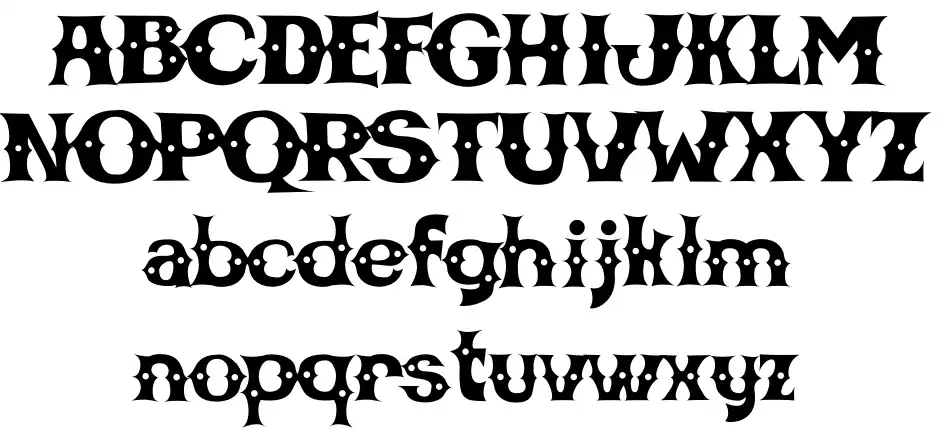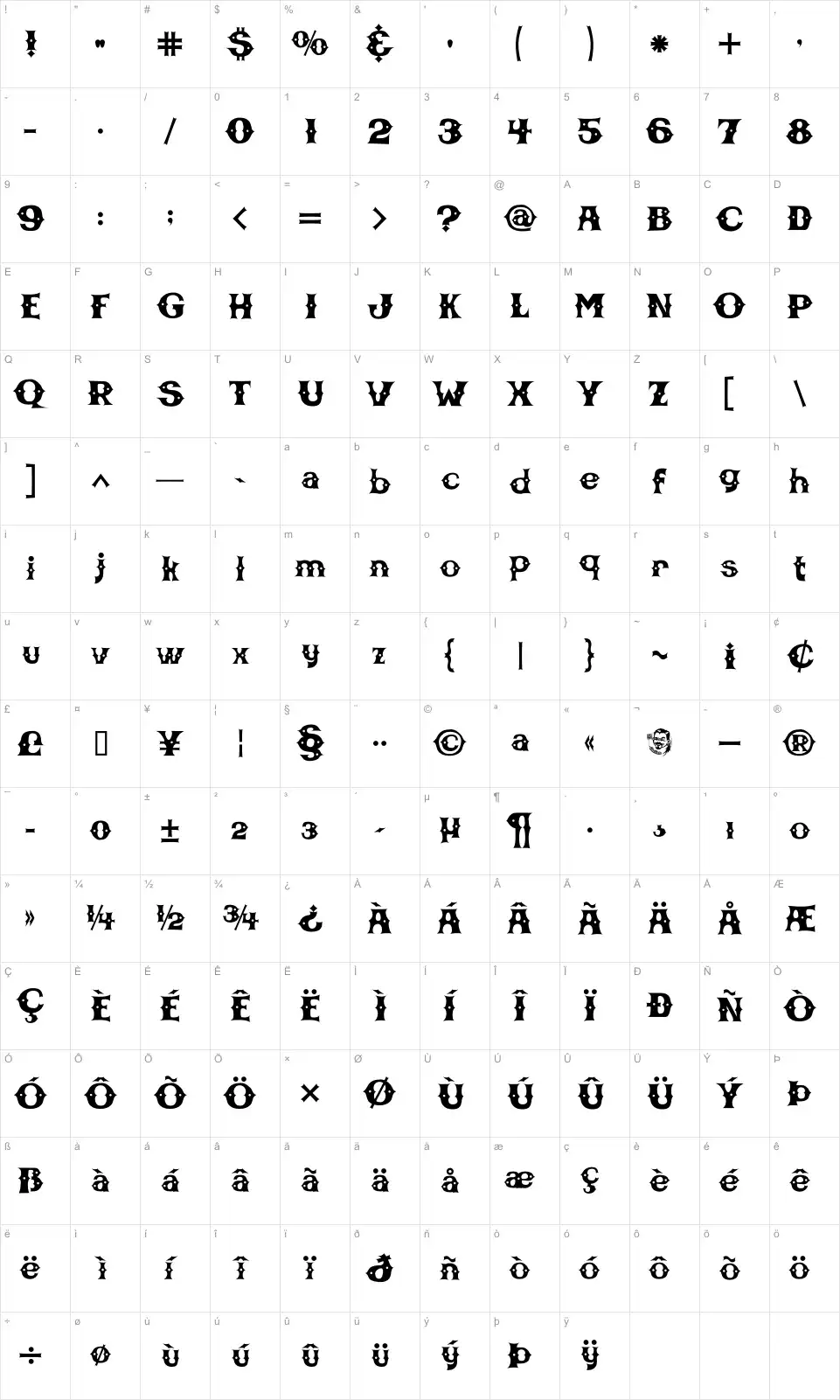
CBGB Font – Download Grátis
A CBGB Font é uma elegante e sofisticada fonte criada pelo designer Gaut Fonts. Sujeitável à utilização para ambientes de design de alta qualidade, esta fonte fica perfeitamente emparelhada com o estilo de lojas de música punk, cinema e outros ambientes de festas glamurosas. Se você busca experimentar o seu efeito personalizado antes de usar, o Gaut Fonts oferece a opção de baixar a fonte ou gerar um preview de texto personalizado online. Com sua categoria de Fancy e seu formato TTF, a CBGB Font é uma excelente escolha para designers que buscam uma fonte de alta qualidade e personalização. Adicionada à plataforma em 11 de julho de 2022, esta fonte já recebeu 1695 downloads, evidenciando sua popularidade entre os designers. Para mais informações ou para adquirir a fonte, você pode visitar o site do designer no endereço http://moorstation.org/typoasis/designers/gaut.
Designer: Gaut Fonts